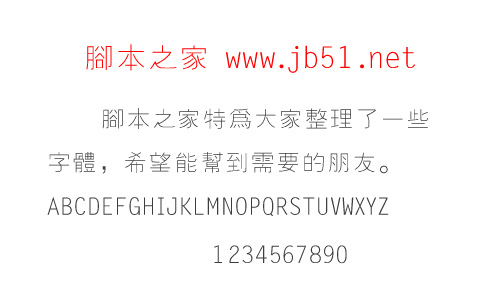
方正幼線繁體字體是方正字體庫(kù)中的一種字體,方正幼線的筆畫纖細(xì),無(wú)喇叭口,一些筆畫交接處特意斷開,口字形結(jié)構(gòu)下部沒(méi)有“伸腿”,布白均勻,成文后的文本灰度較淺。相對(duì)嚴(yán)謹(jǐn)正式的黑體,這款字體則多了一些輕盈的感覺(jué),適用于雜志和書籍中一些情緒放松、個(gè)性柔和的文本。喜歡的朋友們可以前來(lái)下載使用。